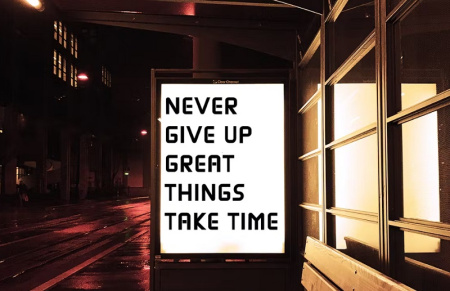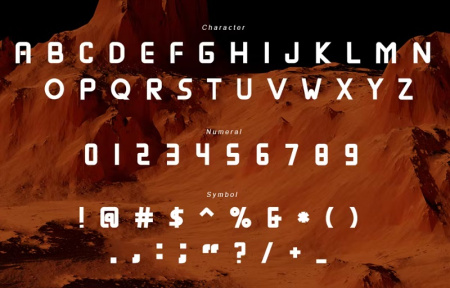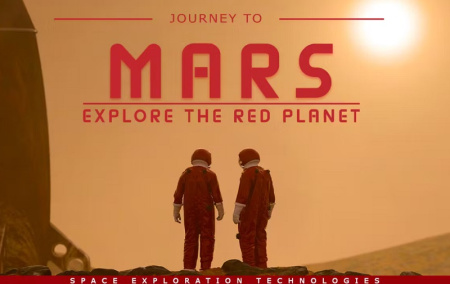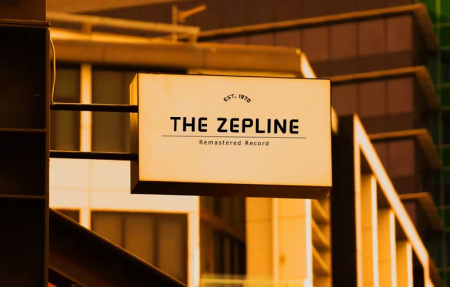
فونت انگلیسی پررنگ Megavox
دانلود فونت پررنگ انگلیسی Megavox
فونت پررنگ انگلیسی Megavox از جی اف ایکس دانلود. یک فونت با حروف کوچک منحصر به فرد است که طراحی شما را مدرن جلوه می‌دهد. شما می توانید از این فونت برای هر هدفی استفاده کنید، به خصوص برای ساخت لوگو تایپوگرافی. قابل استفاده در انواع نرم افزار های طراحی و گرافیکی.
✅ اعداد بزرگ و کوچک نشانه گذاری و علامت